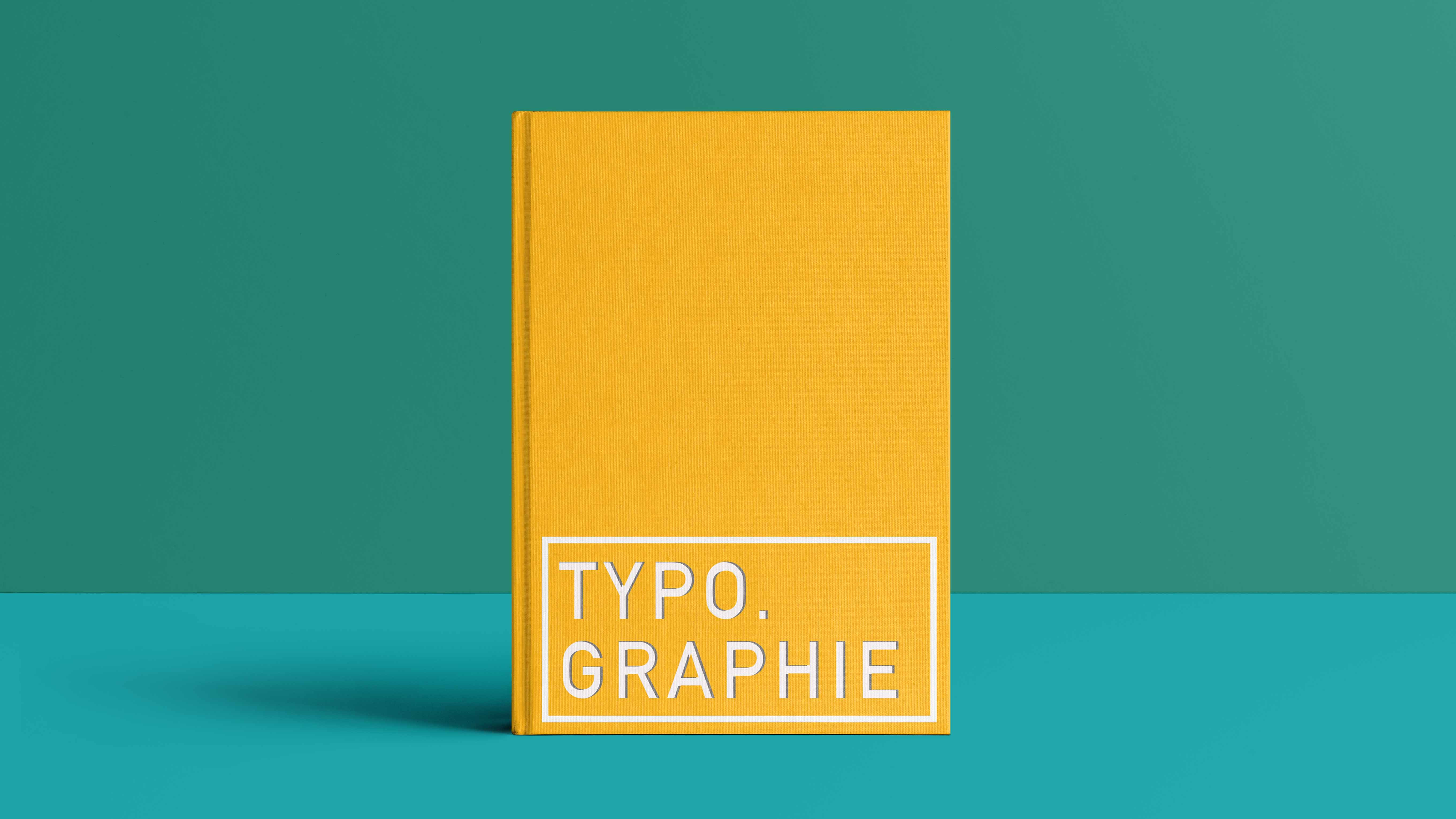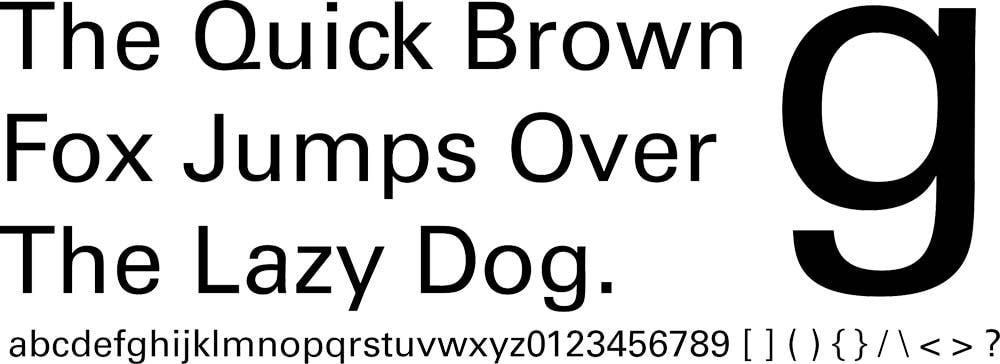
1. Le Guide Ultime de la Typographie
Le Guide Ultime de la Typographie
Styles et familles de polices, supports et historique : Canva vous apprend tout de la typographie !
Agencement des caractères d'écriture, styles et familles de polices, supports et historique : Canva vous apprend tout de la typographie. Ce guide complet vous aidera à comprendre et trouver les typographies qui vous conviendront le mieux.
À l’heure du numérique, il est communément admis que la typographie est une composante essentielle de toute communication visuelle. Aussi importante d’ailleurs, que la photographie ou l’illustration. Les polices de caractères servent — selon leurs agencements — à faire passer différents messages.
Tout d’abord, une mise en contexte s’impose. On parle aujourd’hui de « typographie » pour désigner autant une police de caractères, que les règles de composition qu’on y applique. La « typo », les « règles typos »... des expressions fourre-tout qui méritent d’être affinées. Comment faire le tri ? Canva se propose de répondre à ces questions en vous offrant, une bonne fois pour toutes, un guide référence de la typographie !
1. UN PEU D’HISTOIRE
À l’origine de la lettre : l’alphabet
La typographie concerne donc majoritairement le maniement des lettres, et le sens qu’on peut leur donner. Or, il est bon de s’interroger sur la provenance de ces lettres, et par extension, des alphabets.
Les systèmes de caractères dits « modernes », tel que celui présent en Europe de l’Ouest — l’alphabet latin — utilisent des signes, les lettres, qui configurent les sons dont nous nous servons pour nous exprimer. Ces sons portent un nom bien spécifique : il s’agit des phonèmes.
Ce découpage en unités sonores fut théorisé au début du XXe siècle par le linguiste polonais Jan Niecisław Baudouin de Courtenay.
Les phonèmes peuvent varier fortement d’un idiome à l’autre ; nous avons par exemple 36 phonèmes classiques du français : 16 voyelles, 3 semi-consonnes/voyelles et 17 consonnes.
Cette configuration sera différente selon les langues, même celles utilisant un alphabet commun : il n’y a pas un nombre équivalent de phonèmes pour l’espagnol, l'allemand ou l’italien.
Cette relation directe entre oral et écrit nous semble aujourd’hui être une évidence. Il n’en a bien entendu pas toujours été ainsi.
Les premiers systèmes d’écriture étaient de type pictographique ou idéographique. Les signes les composant représentaient des notions, des idées, voire des objets de manière figurative. L’exemple le plus frappant, et sans doute le plus connu, nous vient des Égyptiens de l’Antiquité. Qui n’a en effet jamais entendu parler des hiéroglyphes ?
Il faudra attendre le 10e siècle av. J.-C. pour voir apparaître les bases d’un système de communication consonantique avec l’alphabet phénicien.
En 2006, l’historienne française et chercheuse au CNRS Françoise Briquel-Chatonnet proposait ce schéma, parfait pour comprendre l’évolution des écritures alphabétiques :
Imprimerie et typographie
Si le terme « typographie » fait référence à l’agencement des caractères d’écriture, il a historiquement plusieurs sens associés et complémentaires.
On peut en effet affirmer sans trop se tromper que la création de la typographie est indissociable de l’invention de l’imprimerie. C’est en Europe, au 15e siècle que l’utilisation de la presse à caractères mobiles (que l’on doit au célèbre Gutenberg) se développe et se démocratise.
Véritables petites corporations, les ateliers emploient des maîtres et compagnons imprimeurs aux tâches bien définies : le « prote », chef d’équipe conçoit et dessine les caractères. L’ouvrier fondeur les moule dans un alliage de plomb, tandis que le « singe », spécialisé dans la mise en page, dispose ces mêmes caractères sur sa grille pour former le texte destiné à être imprimé. Enfin, le compagnon chargé de la lourde presse à bras (l’ours) s’assure de la bonne réalisation de la page en cours.
À la lumière de ces explications, on comprend que la « typographie » désigne historiquement :
• le dessin des familles de caractères appelés « polices »
• les règles qui régissent l’utilisation de ces caractères, les « règles typographiques »
• l’agencement et la bonne disposition de ces caractères, la « mise en page »
Attention toutefois à ne pas confondre la typographie, qui désigne l’utilisation de lettres déjà formées dans le cadre d’une technique particulière (imprimerie, PAO…) avec la calligraphie ou le lettering (tracés manuels de lettres dans un but esthétique).
→ La découverte de la typo et de ses applications n'a jamais vraiment de fin car c'est un domaine en constante évolution. À vous d'en comprendre les enjeux, de les appliquer à vos projets... et de foncer !